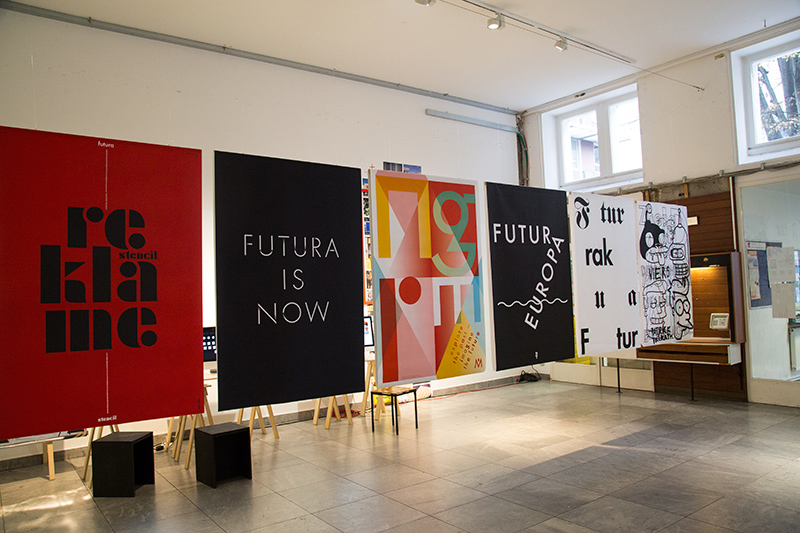
Symposium Translations 5 »Tribute to a Typeface«
Vergangenen Freitag, am 04.11.2016, fand in der FH Mainz das Symposium Translations 5 »Tribute to a Typeface« statt. Die Symposiums-Reihe »Translations« des Studiengang Kommunikationsdesign diskutierte neue designhistorische Forschungsergebnisse zur Entstehungs- und Rezeptionsgeschichte der FUTURA. Vorgestellt wurden zudem aktuelle Positionen im Type und Corporate Design, die sich auf die berühmte geometrische Sans Serif beziehen oder aber sich dezidiert von ihr abwenden.
Diese starteten gleich darauf mit dem ersten Vortrag »FUTURA. Tribute to a typeface«, der sich um das Gesamtprojekt FUTURA. DIE SCHRIFT. drehte, welches als Kooperationsprojekt zwischen dem Gutenberg-Museum Mainz und dem Institut Designlabor Gutenberg der Hochschule Mainz entstanden ist. Passend zum 90-Jährigen Jubiläum der Futura, haben Isabel Naegele und Petra Eisele zusammen mit Dr. Annette Ludwig, der Direktorin des Gutenberg-Museums, drei Jahre lang die Entstehung und Verbreitung der Futura erforscht. Dabei entdeckten sie bisher unveröffentlichte Skizzen und Schriftproben der Futura, welche man in der Ausstellung »FUTURA. DIE SCHRIFT.« im Gutenberg-Museum Mainz noch bis zum 30. April 2017 betrachten kann. Zudem ist aus dem Forschungsprojekt ein 520 Seiten starker Katalog mit zahlreichen farbigen Abbildungen und Schriftproben entstanden, welcher beim Verlag Hermann Schmidt Mainz erschienen ist. Außerdem haben Isabel Naegele und Petra Eisele eine Sonderedition mit dem Titel »TRIBUTE TO PAUL« herausgegeben, welche visuelle Statements von international bekannten Designern wie Lars Harmsen, Erik Spiekermann und Ferdinand Ulrich, Erwin K. Bauer, Neil Donnelly, Jakob Runge, Vier5, Trafik und vielen weiteren enthält.
An zweiter Stelle sprach an diesem Tag der spanische Designer Pere Alvaro von »Bis« aus Barcelona. Sein Vortrag trug den Namen »FUTURA IS NOW«. Sein, 1997 mit Alex Gifreu, gegründetes Büro konzentriert sich stark auf die Kommunikation innerhalb der Kulturindustrie, ganz besonders öffentliche Einrichtungen wie Museen und Galerien. Das Büro befindet sich in Barcelona, aber die Kunden stammen aus ganz Spanien sowie aus dem restlichen Europa und Amerika. Alvaro berichtete davon, dass Bix des Öfteren mit der Futura gearbeitet hatte. Unter anderem setzen sie die Schrift für geometrische Corporate Designs ein. Die Schrift stellt für sie eine gestalterische Revolution dar. An der Futura schätzt Bis besonders ihre Einfachheit, Wirtschaftlichkeit, Modularität, starken Charakter und ihre Einzigartigkeit.
Nach einer kleinen Pause ging es schließlich weiter mit dem Vortrag »Paul Renner – the man behind Futura« des Typographen, Schriftdesigners, Designhistorikers und absoluten Paul Renner-Experten Christopher Burke aus Reading. Burke sprach über Paul Renners Leben und seinen Werdegang sowie seine Zeit in Frankfurt, welche zur Entstehung der Futura beitrug und Renners Stil beeinflusste. Zudem sprach Burke über Renners und Jan Tschicholds Verhältnis zueinander und die Gründe für die Popularität der Futura.
Von einer ganz anderen Perspektive aus sprachen die Art-Direktorinnen Stefanie Barth und Carina Frey, im nächsten Vortrag »An example of image and typography – double magazine and other projects in fashion and design« über die Futura. Beide geben an »keine Typographen« zu sein, sondern aus Mode-, Kunst- und Bewegt-Bildbereichen zu kommen. Stefanie Barth und Carina Frey arbeiten in Paris und Mailand für Kunden wie Céline, Hermès und Dior Beauté sowie für eine Reihe von Marken und Boutiquen rund um den Globus. Auf dem Symposium stellten sie ihr Magazin »double« vor, welches nach einem Redesign die Futura als Corporateschrift hat. Dabei kombinieren sie die geometrische Grotesk auf 320 Seiten immer wieder mit anderen Serifenschriften und setzen sie zu zeitgenössischer Modefotografie.
Nach einem kleinen Lunch ging es gegen 14 Uhr weiter mit einem Kurzvortrag von Sarah Schmitt, Christian Weber und Axel Becker, welche im Masterstudiengang Gutenberg-Intermedia eine partizipative Bildplattform mit dem Namen »type-trap« ins Leben gerufen haben. Es ist die weltweit größte Suche nach der Schrift Futura: auf Plakaten, Neonreklamen, Schildern, Verpackungen, Bücher, Visitenkarte, Tattoos, etc. – zuhause, in der Stadt und auf dem Land. Jeder ist eingeladen, dort seine Fundstücke hochzuladen und darüber zu berichten. Man kann mittels eines Rankings sehen, in welcher Stadt zur Zeit am meisten Fundstücke hochgeladen wurden.
Jakob Runges knackiger und auf den Punkt gebrachter Vortrag »Der Custom Font und die Geometrie« folgte darauf. Als begeisterter schwarz-weiß-Spezialist, entwirft Jakob Runge Fonts und maßgeschneiderte Corporate Schriften bei TypeMates. Einige davon stellte er an diesem Freitag vor. Darunter eine seiner ersten Schriften, die »Edelsans«, welche eine Mischung aus der Futura und der Avenir war. Daraus entwickelte er dann den Costum Font »Lenbach Grotesk« für das Lenbachhaus in München. Zudem zeigte Runge seine Schrift »Cera«, welche ebenfalls eine geometrische Serifenlose und mit der Futura verwandt ist. Diese entwickelte er zudem als Brushfont und als Stencil-Schnitt.
Mit dem Vortrag von Iva Knobloch aus Prag mit dem Thema »Futura as a geo-political matter in the Czech Lands« wurde es wieder designhistorischer. Knobloch arbeitet als Kuratorin der Sammlung von Drucken am Museum für Dekorative Kunst in Prag und lehrt Geschichte des Grafikdesign an der Akademie für Kunst, Design und Architektur in Prag. In ihrem Vortrag sprach sie über das »Typografia Magazine« welches in den 20/30er Jahren eine wichtige Rolle in der tschechischen Designwelt spielte. Außerdem zeigte und sprach Knobloch über bekannte und wegweisende Werke der tschechischen Gestalter Ladislav Surnar, Zdeněk Rossmann, František Kalivoda und František Muzika.
Weiter ging es schließlich mit einem Vortrag des Hamburger Designbüros »I LIKE BIRDS«, gegründet von André Gröger und Susanne Kehrer – Alumni der FH Mainz. Das Team beschäftigt sich mit der Umsetzung von Designideen in kreative Produkte. Schwerpunkt der Arbeit ist die Transformation einer Vielfalt an Informationen in visuelle Sprache, die die Inhalte in flüssiger und effektiver Art und Weise durch eine Vielzahl von Printmedien transportiert. Mit ihrem Vortrag »Past and Futura« sprachen sie sich kritisch zum Gebrauch der Futura aus. Bisher haben sie die Futura nicht für ihre Arbeiten benutzt, da sie ihnen zu überreizt vorkommt. Durch die gute Anpassungsfähigkeit der Schrift wird sie für I LIKE BIRDS zu beliebig und besitzt eine geringe Individualität. Das Team entwirft lieber selber Schriften, welche einen eigenen Charakter besitzen, überraschen und individuell auf ihren Kunden abgestimmt sind. Dabei arbeiten sie sehr spielerisch und experimentell.
Der Vortrag des Ausstellungsleiters und Kurators für Design und stellvertretender Direktor am Museum Angewandte Kunst in Frankfurt a. M. sowie Professor für Designtheorie und -geschichte an der HfG Offenbach Klaus Klemp, behandelte das Thema »Hans Leistikow und der Versuch eines Corporate Design für das Neue Frankfurt«. Er sprach über die politischen und wirtschaftlichen Hintergründe, sowie gesellschaftlichen Fügungen welche zum neuen Visual des Neuen Frankfurts führten. Ein Protagonist darunter: Paul Renner. Des weiteren sprach Klemp über die Arbeit Hans Leistikows, welcher ein neues Corporate Design zu jener Zeit entwickeln sollte. Klaus Klemp hat zahlreiche Publikationen zu Architektur, Design und Bildender Kunst veröffentlicht.